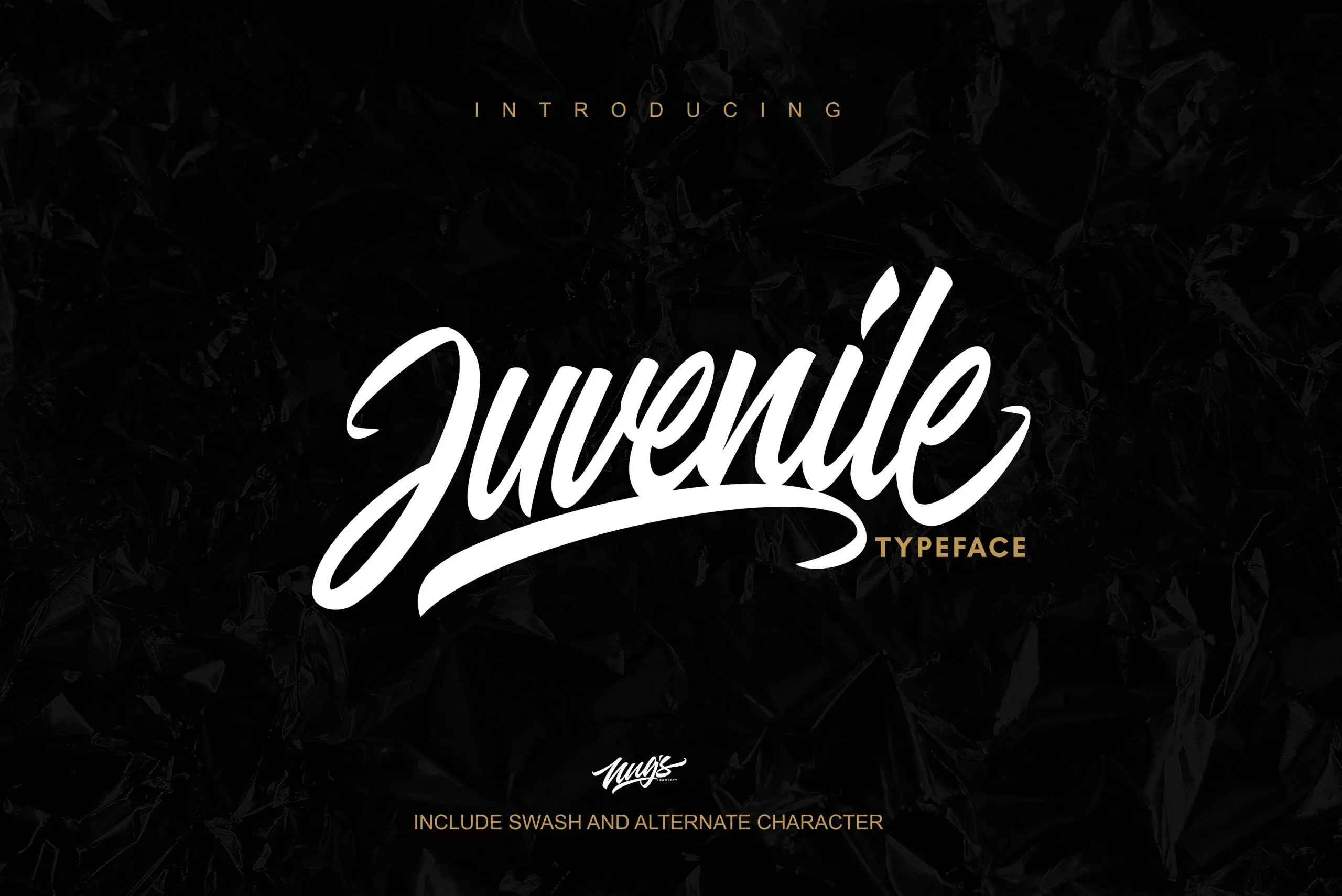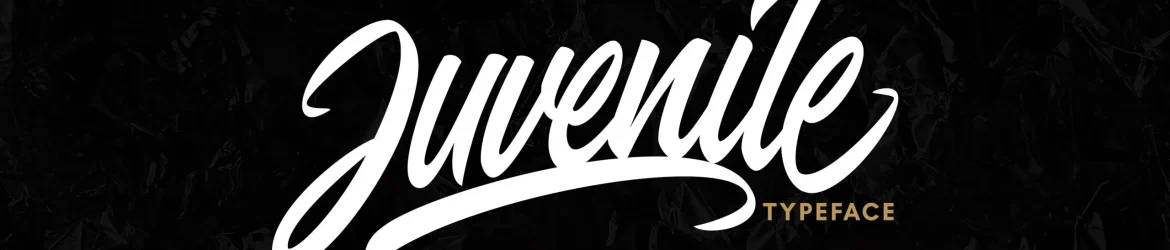
A Juvenile Script Font é uma escolha perfeita para quem busca estilo moderno no seu design. Desenhada por NUGS, esta fonte script apresenta uma aparência artesanal e rústica, com um toque de letra a mão e estilo de pincel. Ela se destaca em diversas aplicações gráficas, desde logotipos e embalagens de produtos até cartões de felicitações e panfletos. A fonte oferece uma completa gama de letras maiúsculas e minúsculas, num total que inclui números, pontuação e ligaduras. Ela também está equipada com suporte para múltiplas línguas, tornando-a versátil em qualquer projeto gráfico que você possa imaginar. Com o Juvenile Font, suas criações ganharão um toque pessoal e autêntico, sem esforço algum.